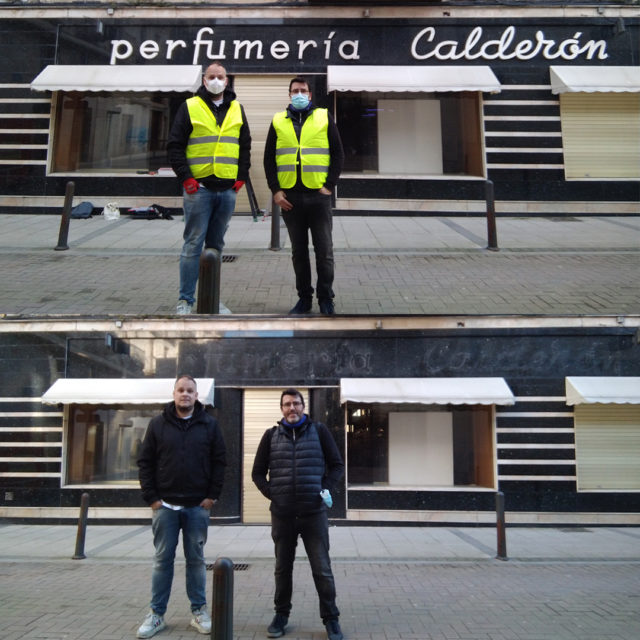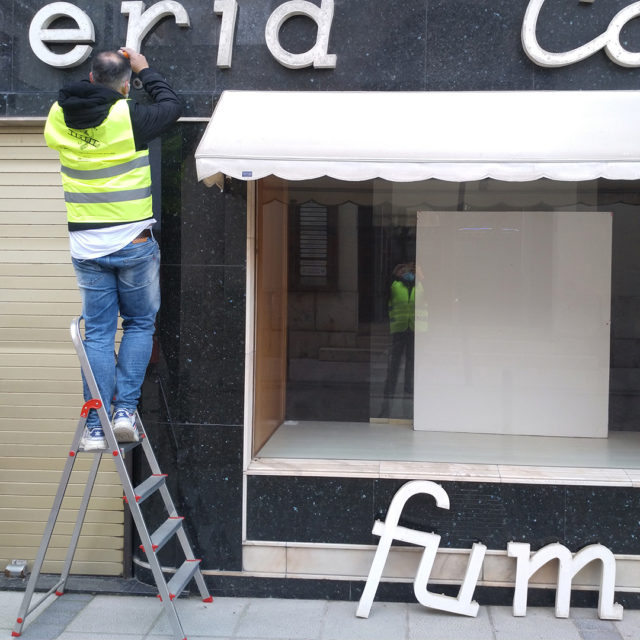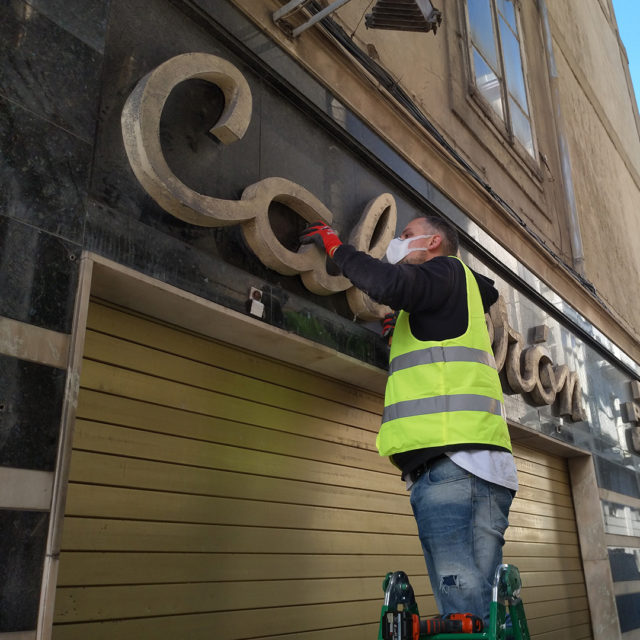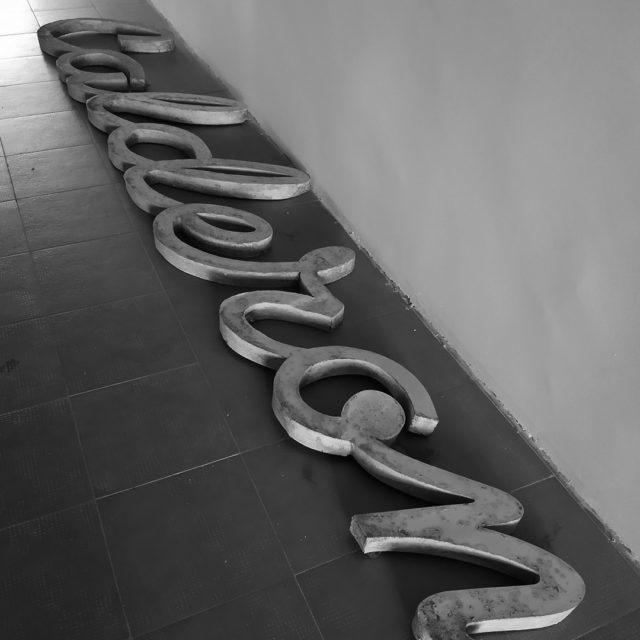
Salvado el rótulo de Perfumería Calderón
Ayer pudimos bajar los rótulos de la centenaria Perfumería Calderón. Cerró definitivamente el 31 de octubre de 2021 tras cumplir ese verano 100 años. Fundada en 1921 como droguería (de las primeras en Santander) se ubicó inicialmente en el edificio junto a la sede del Banco Santander, cuando este la amplió, se trasladaron a la ubicación actual.
El rótulo de gran formato es de esa época, en torno a los años 50, y se caracteriza por la combinación de dos tipografías en palo seco y script. Diseño que también ha servido para ser la imagen gráfica de la perfumería en los distintos soportes.
El desmontaje ha sido posible gracias a la familia propietaria, Luisa y Ricardo Calderón, que conocedores del proyecto, han donado esta pieza para su preservación.
Patrimonio Gráfico en riesgo
No es habitual que esto ocurra. Normalmente cuando se inician las obras de los locales comerciales, los rótulos suelen acabar en la basura como chatarra o vendidos en páginas de venta de segunda mano como objetos de decoración. Como fue el caso de “La Mejillonera” (1974) por ejemplo, que fue destruido después del confinamiento y el aviso llegó tarde.